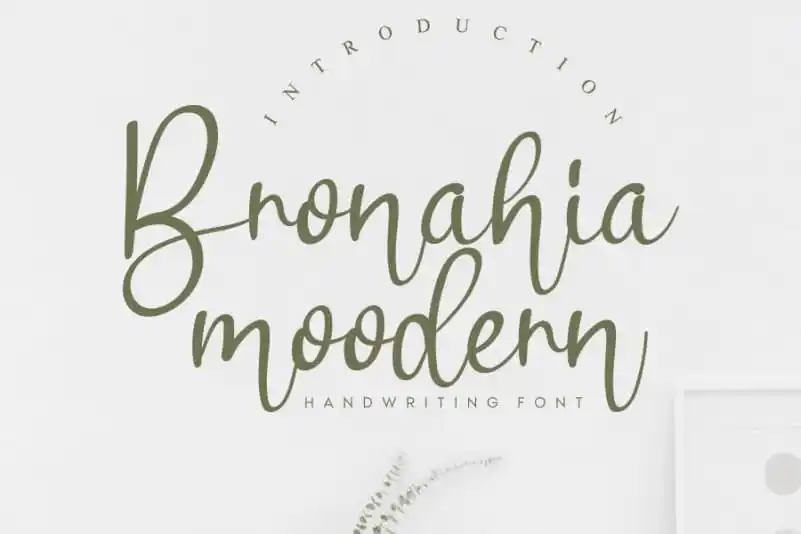
Bronahia Handwritten Font
A fonte Bronahia Handwritten é uma criação única que transmite ao usuário a sensação de escrita à mão real. Com letras redondas e com um toque contemporâneo, ela incorpora influências clássicas do calligrafismo enquanto se apresenta como uma opção fresca para projetos digitais atuais. Desenvolvida com mestria, Bronahia é perfeita para quem busca a elegância tradicional do grafite combinada com a modernidade de um estilo à mão livre. Este é o tipo certo para aqueles que desejam dar vida e personalidade aos seus projetos digitais. Com apenas alguns cliques, você pode transformar qualquer página em uma verdadeira obra-prima de design. Atribua uma pitada de elegância ao seu próximo projeto com Bronahia Handwritten Font, e deixe sua identidade digital ser reconhecível e única.